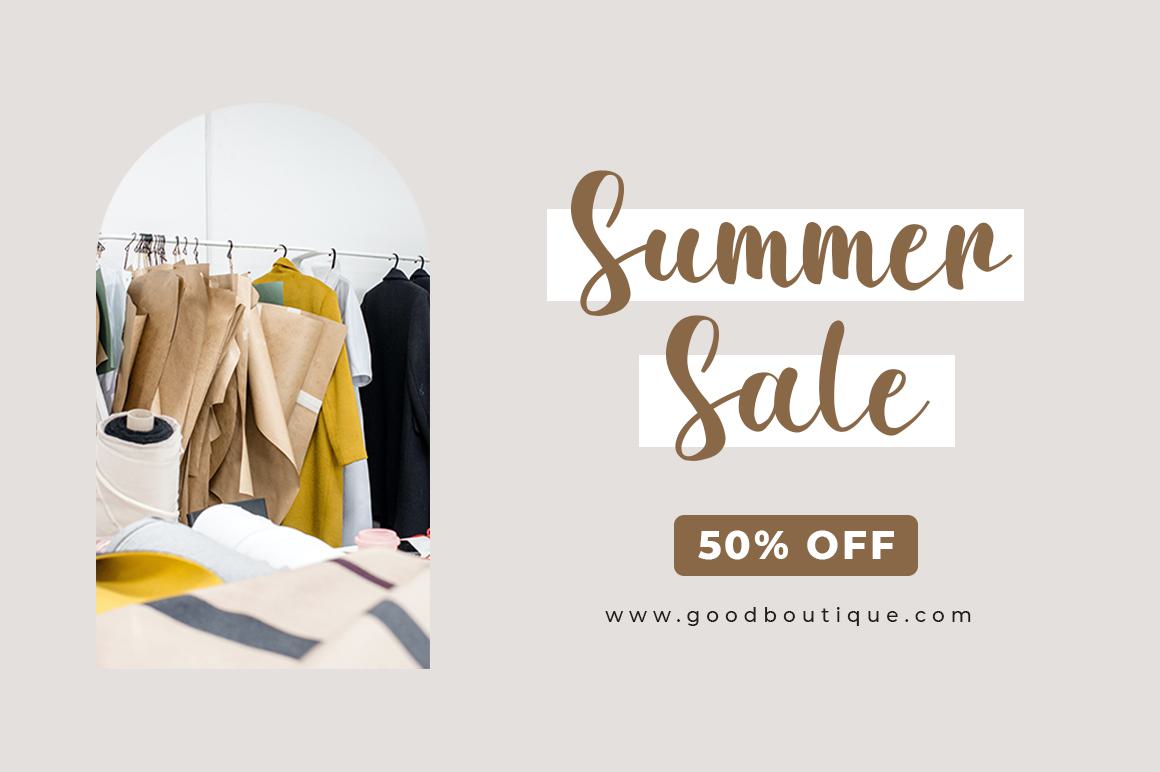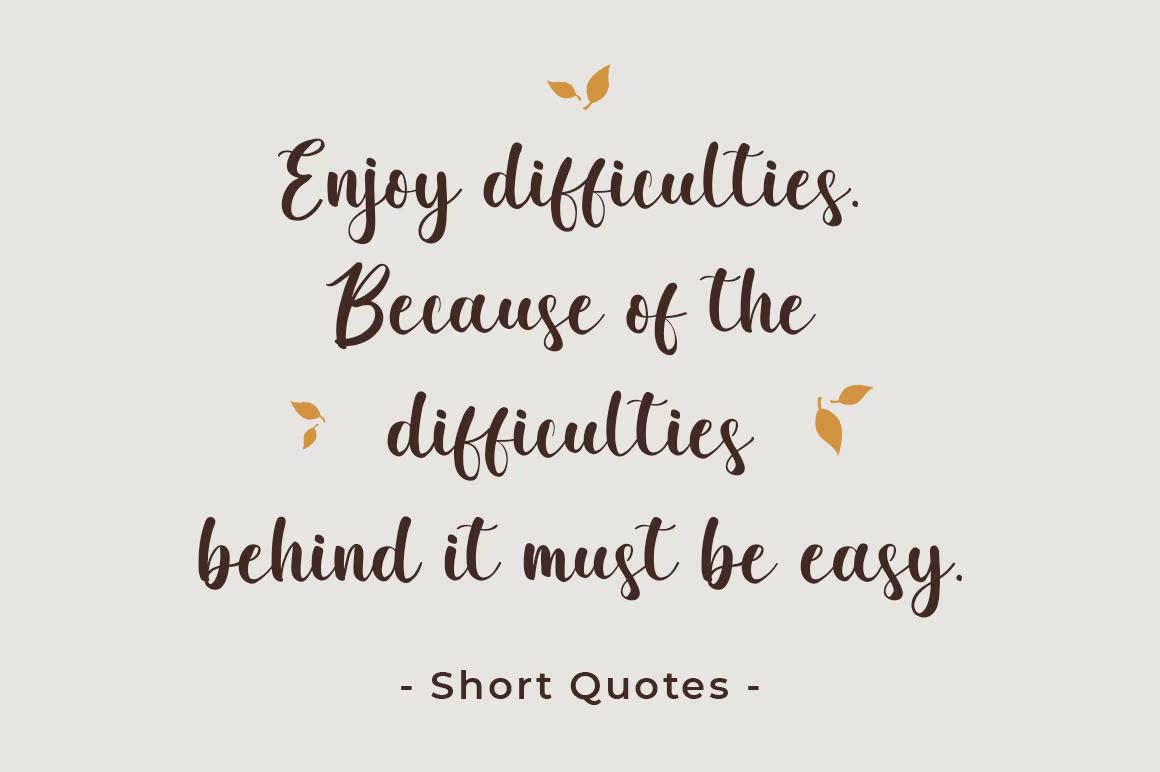
BeautySaharais Sweet Font and Modern Alligraphy with AbeautyFeel.其独特的圆形字母表示该Fontamasterece.BeautySaharais Sweet Font and Modern Alligraphy with AbeautyFeel.其独特的圆形字母表示该Fontamasterece.其独特的圆形字母表示该Fontamasterece。